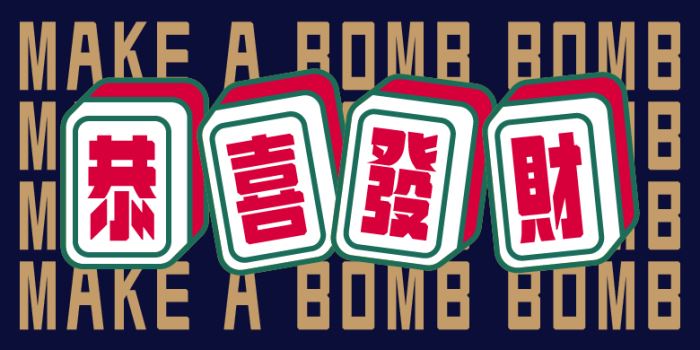
方正復(fù)古粗黑簡(jiǎn)體由方正字庫(kù)張雪煒設(shè)計(jì)師出品的藝術(shù)字體,該字擁有高挑的身形,“橫”的筆畫邊角做了直角切割處理,讓筆畫處理不顯單調(diào),適合應(yīng)用于藝術(shù)設(shè)計(jì)、平面宣傳設(shè)計(jì)、網(wǎng)頁(yè)設(shè)計(jì),書法等領(lǐng)域。
字體介紹
這是一款與常規(guī)黑體設(shè)計(jì)“橫細(xì),豎粗”特點(diǎn)不同的字形,這款字形主打“橫粗,豎細(xì)”,字形擁有高挑的身形,“橫”的筆畫邊角做了直角切割處理,讓筆畫處理不顯單調(diào)。為了避免全直角筆畫太過生硬的感覺“撇、捺”筆畫使用柔美的曲線代替,整體筆畫結(jié)構(gòu)借鑒了老字形的部分特點(diǎn),融合為一款全新的“方正復(fù)古粗黑”。